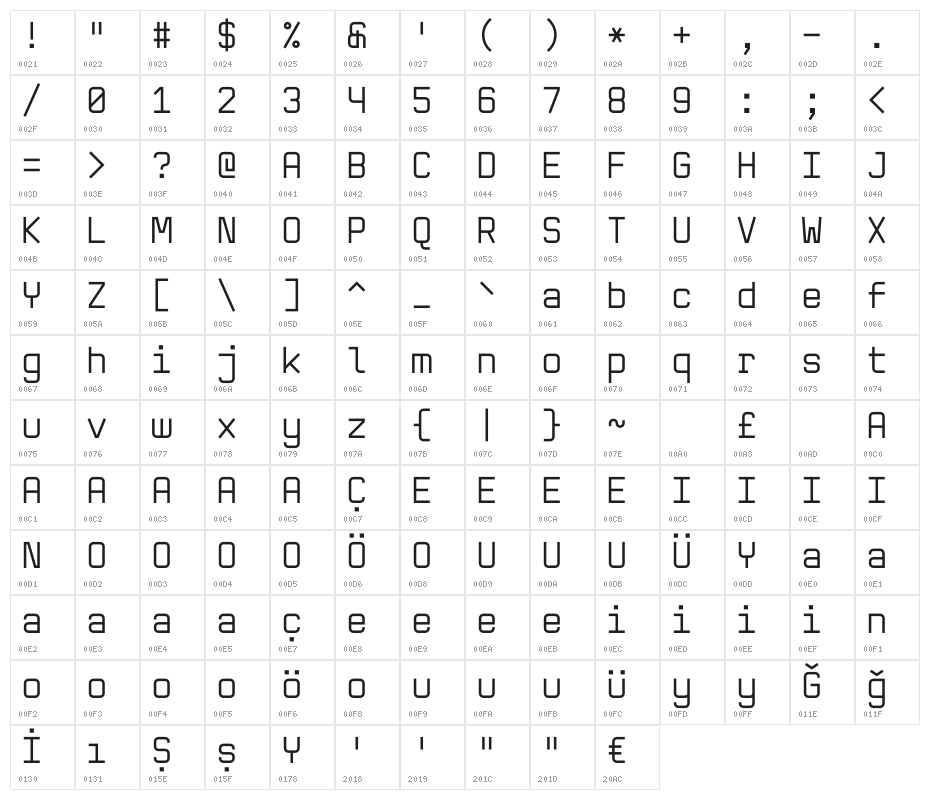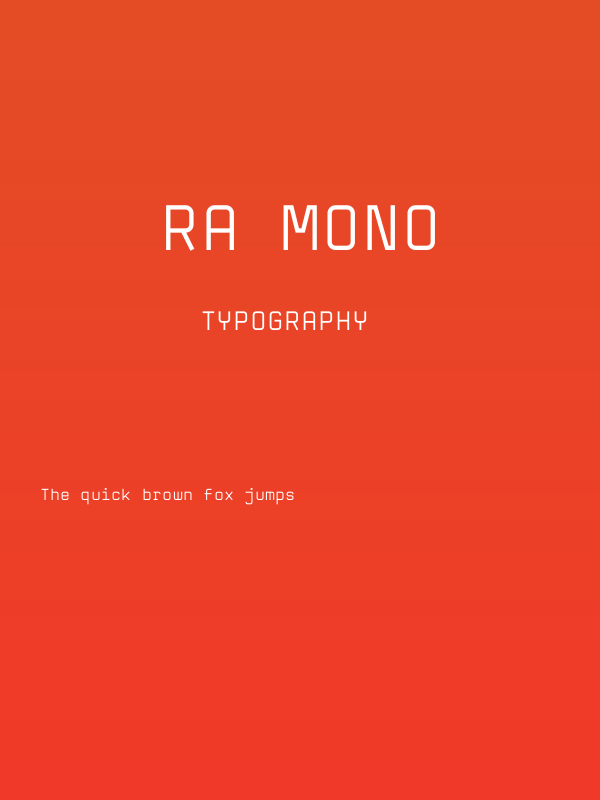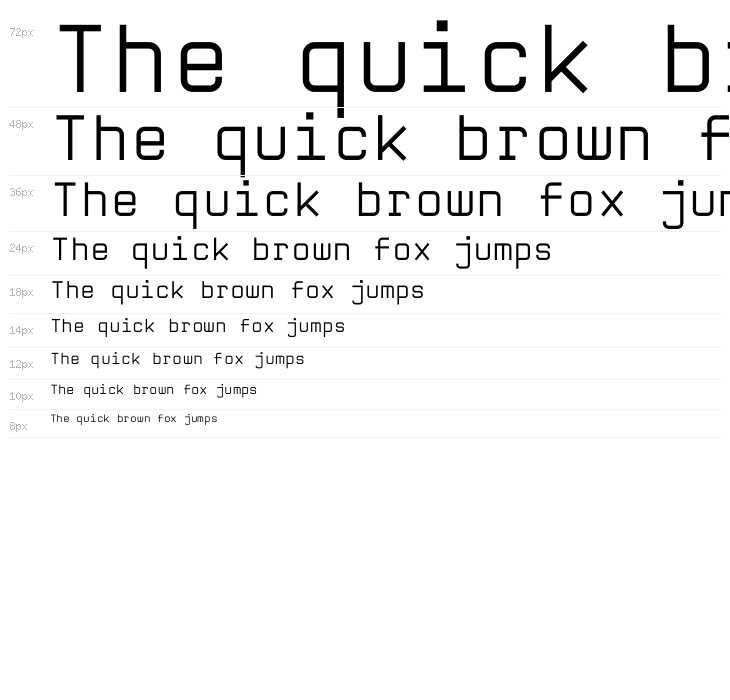
Ra Mono Font
| Caso d'uso | Coding, Technical documentation, User interfaces |
| Progetti proposti | Ideal for coding, technical documentation, and any project requiring clear, uniform text presentation. |